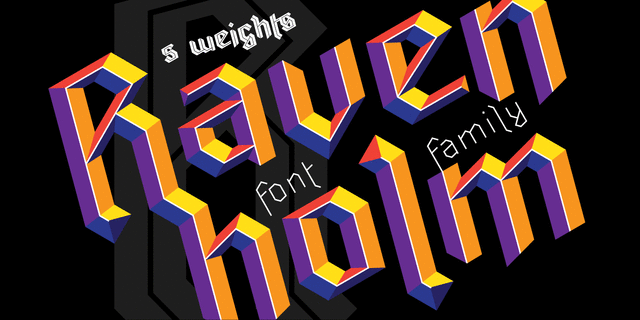
Ravenholm – это современное готическое шрифтовое семейство. Шрифт выглядит потрясающе как в виде отдельных слов, так и в текстовых блоках. Поддерживаются многие языки: чешский, датский, норвежский, немецкий, английский, испанский, французский, итальянский, венгерский, голландский, португальский, финский, шведский, турецкий, русский и т. д. Ravenholm имеет 5 начертаний, включая цветной шрифт OTF Color Font.
Шрифт разработал Андрей Дыкун в 2019 году.